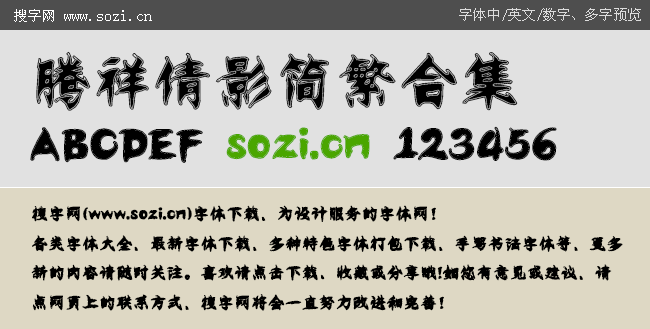
騰祥倩影簡繁合集
搜字網(wǎng)提供一款騰祥倩影簡繁合集中文藝術(shù)字體下載,騰祥倩影體是一款由手寫風(fēng)格的書法字體修改的藝術(shù)字體,字體大方得體,效果非常漂亮,可以應(yīng)用于橫幅標(biāo)語、美術(shù)設(shè)計(jì)、宣傳海報(bào)、圖形設(shè)計(jì)等領(lǐng)域。